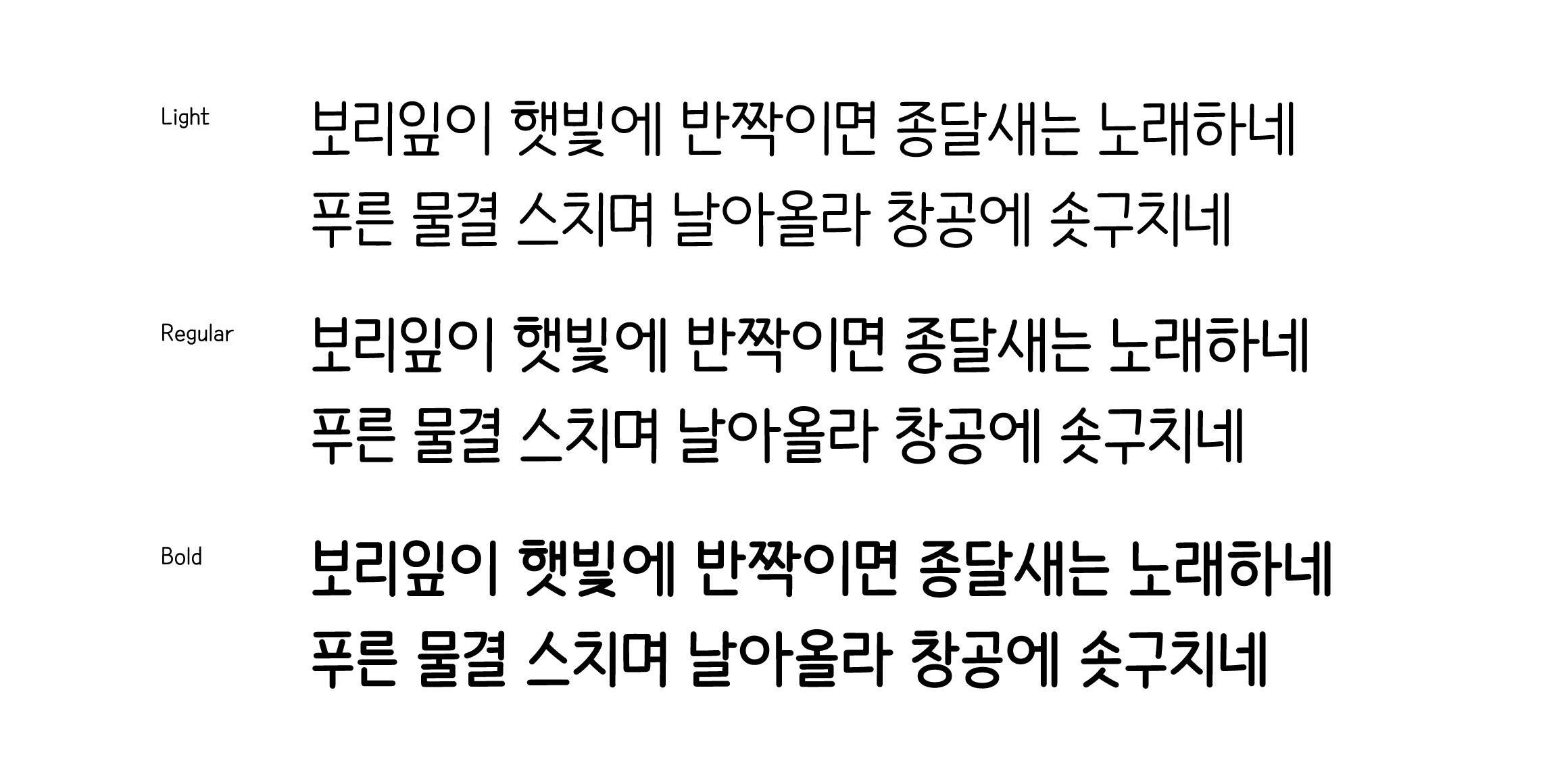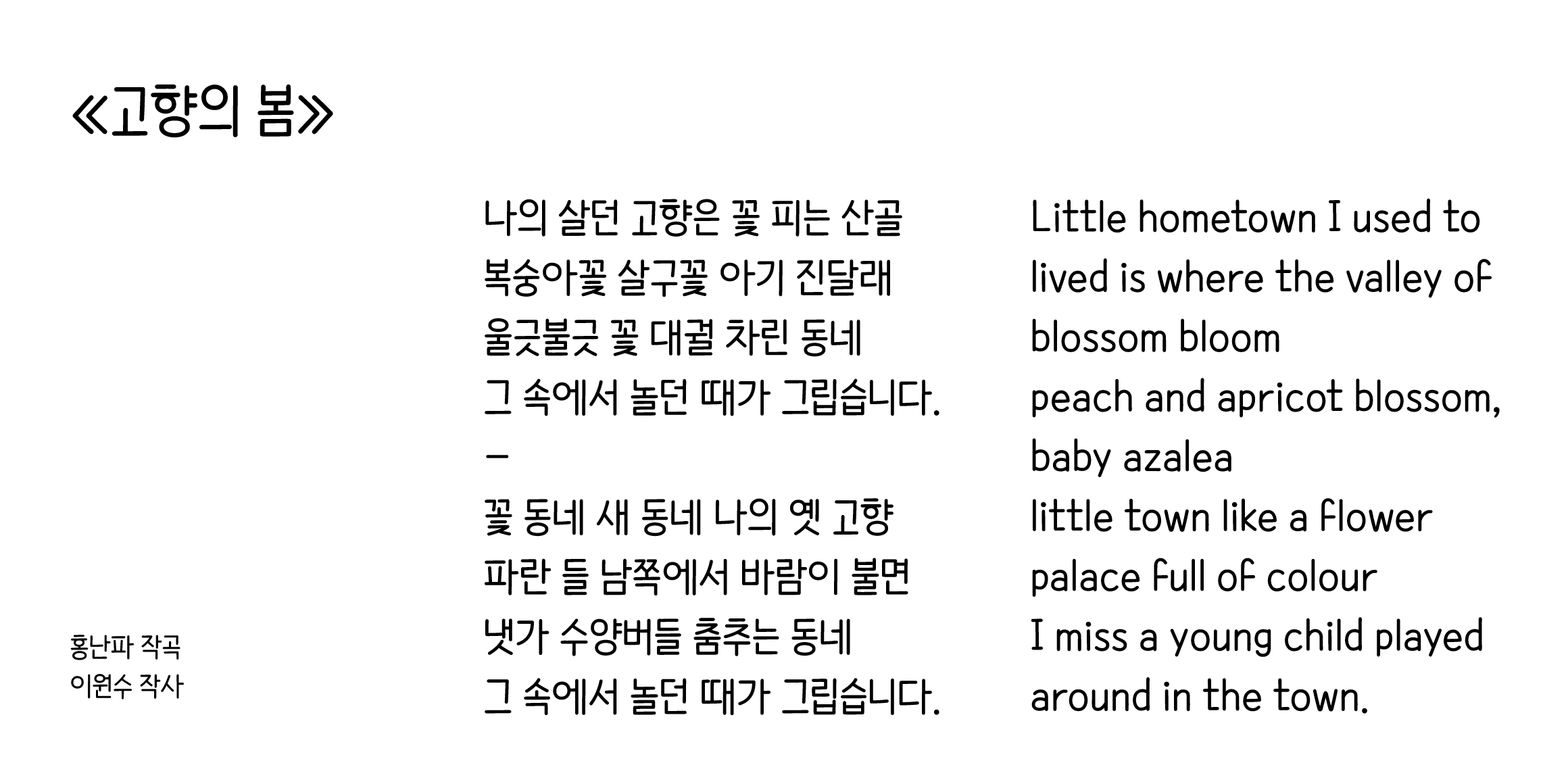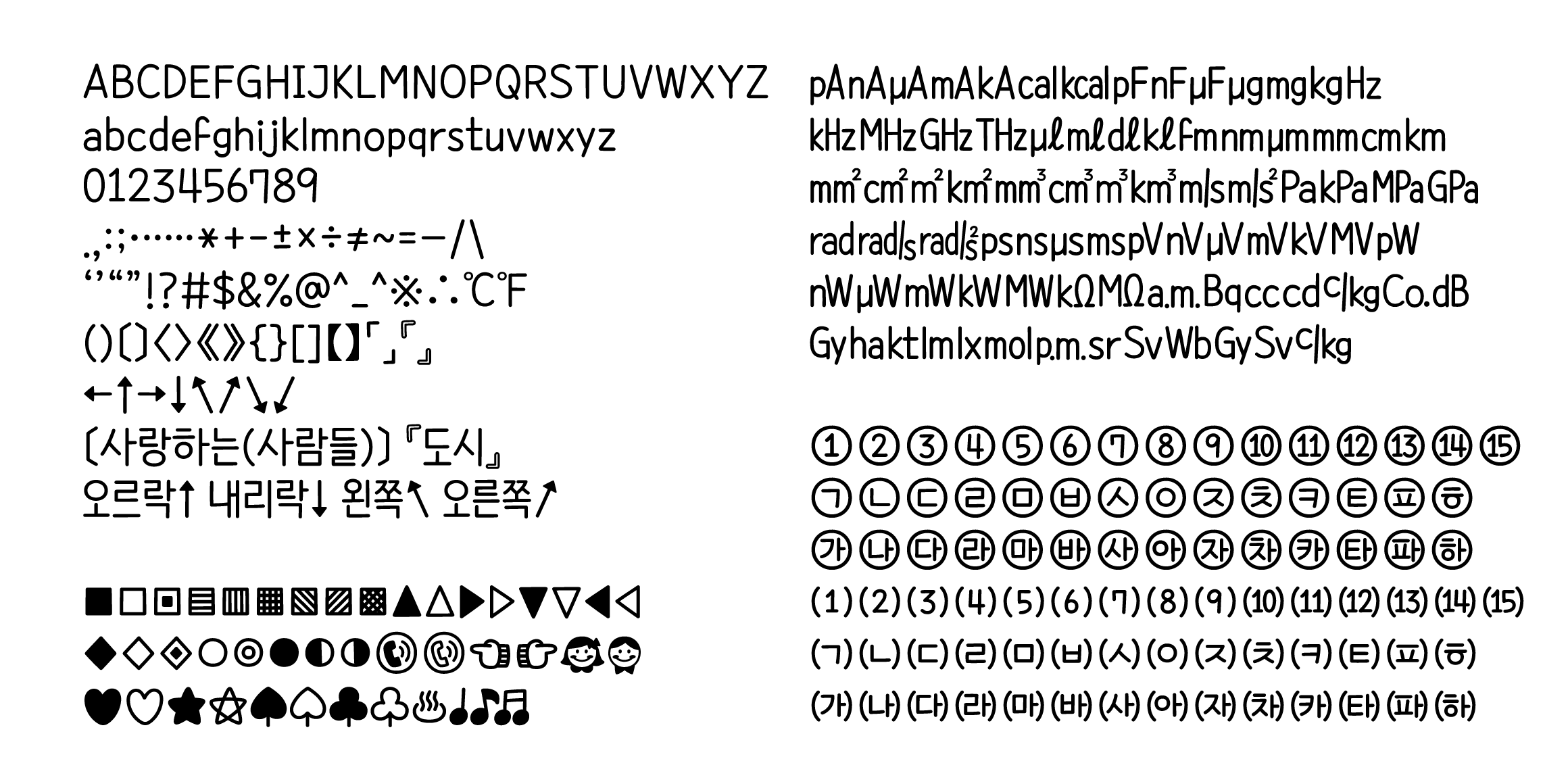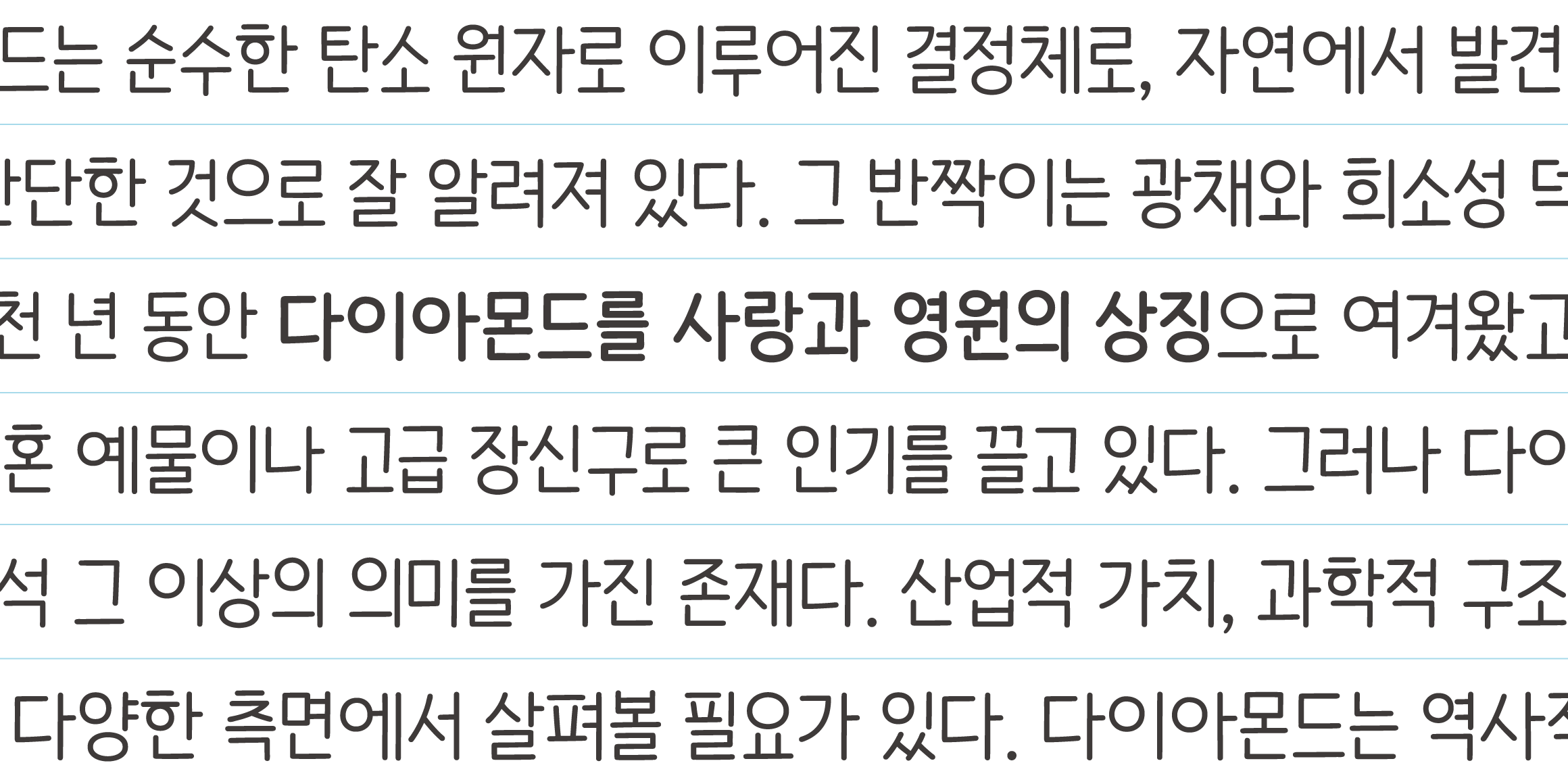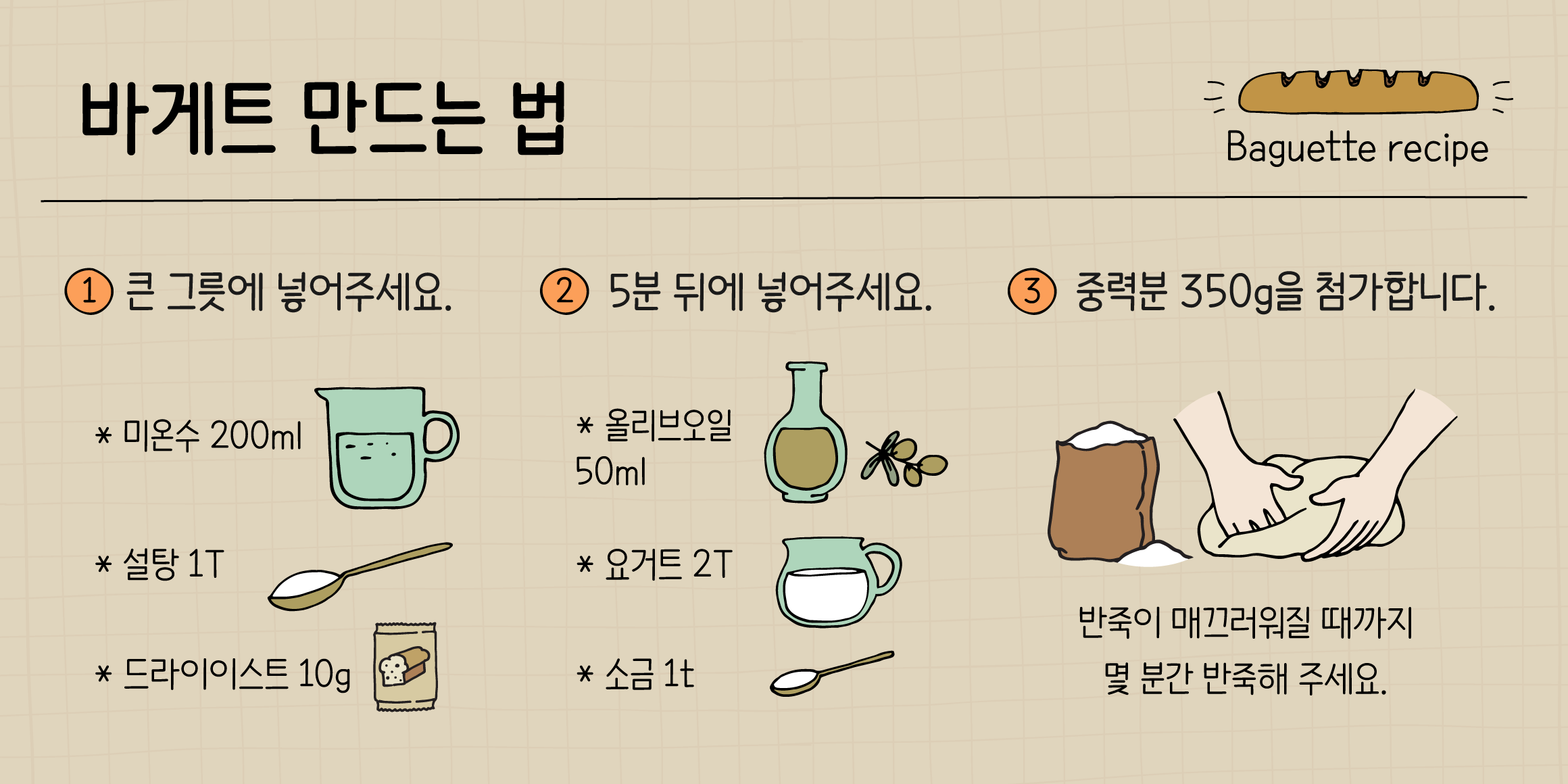
And바른생활고딕2
분류 Sans,Script,디스플레이,민부리
제목용본문용현대적
• Light
• Bold
And바른생활고딕2 font in use
And바른생활고딕의 두 번째 버전입니다. And바른생활고딕의 탈네모틀 구조를 꽉찬 네모틀 구조로 변경했습니다. 자소의 크기감과 글자를 구성하는 자소 사이사이의 공간이 기존 And바른생활고딕보다 균일합니다. 글자모임꼴마다 다르던 초성 ‘ㅅ,ㅈ,ㅆ,ㅉ,ㅊ’의 형태를 동일하게 통일했습니다.